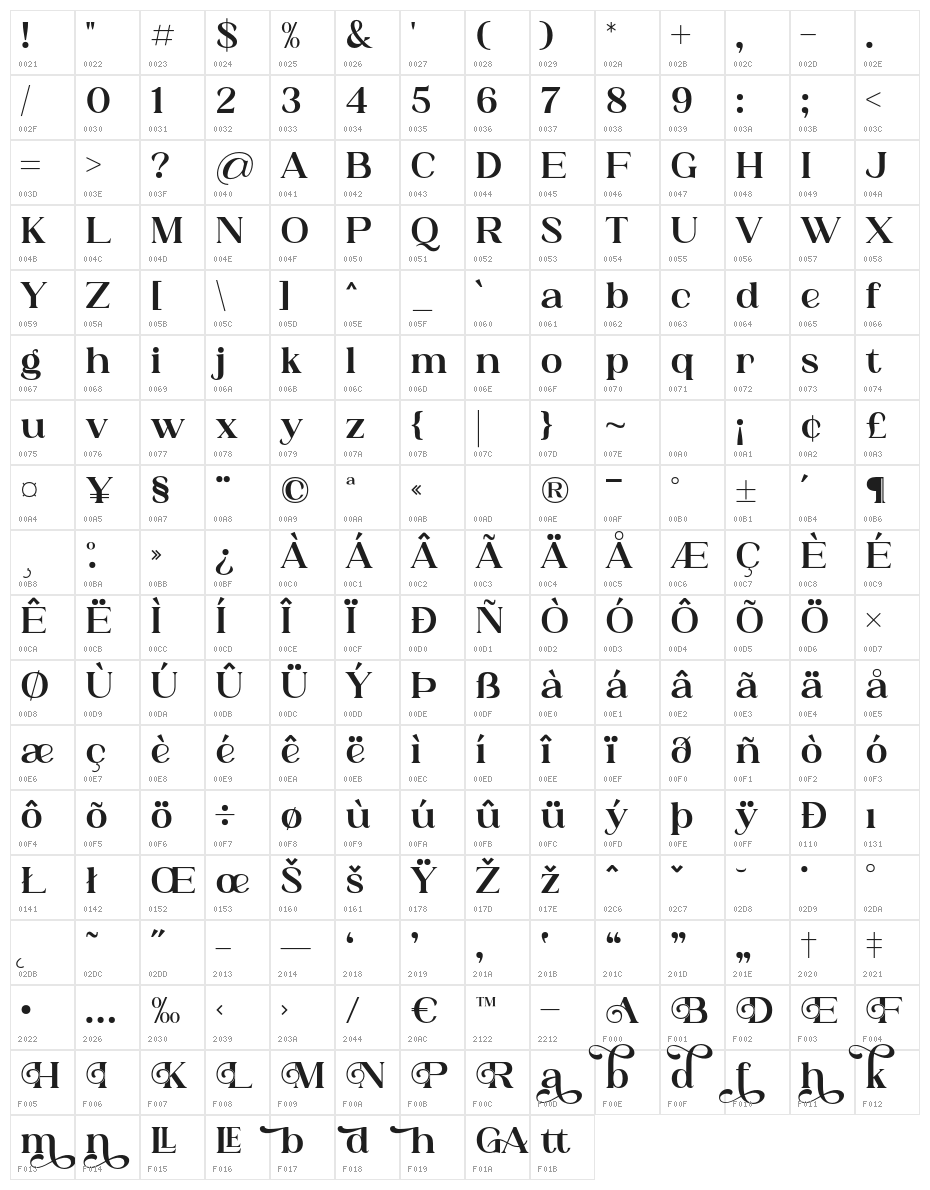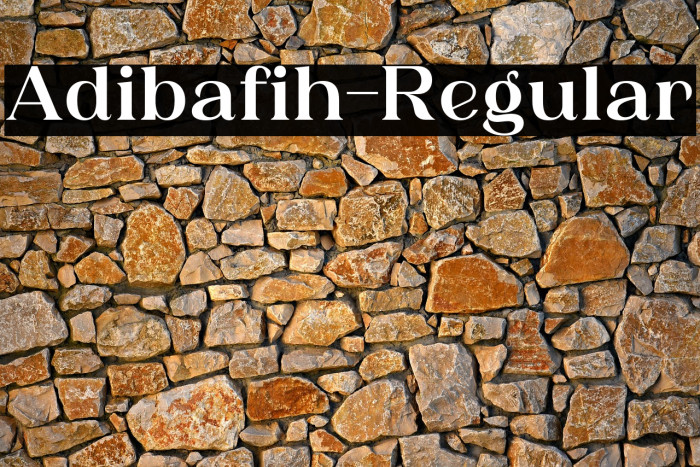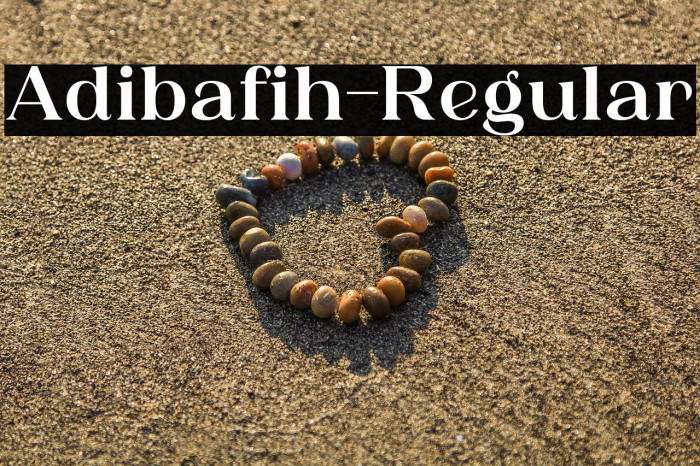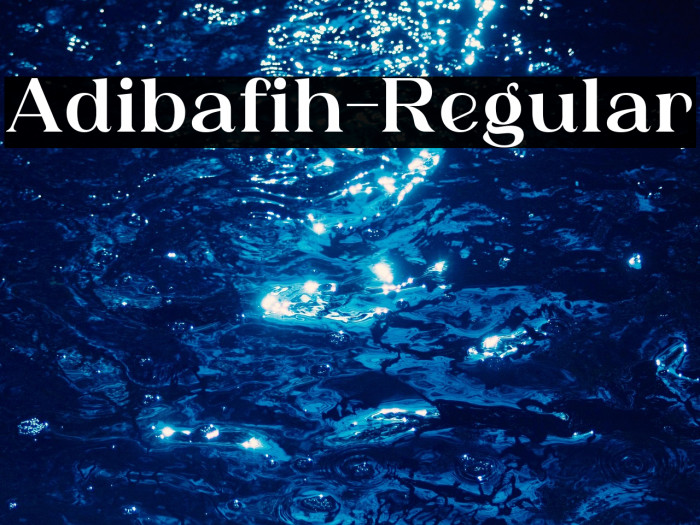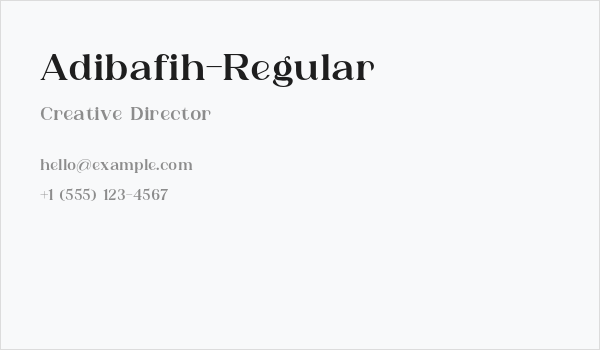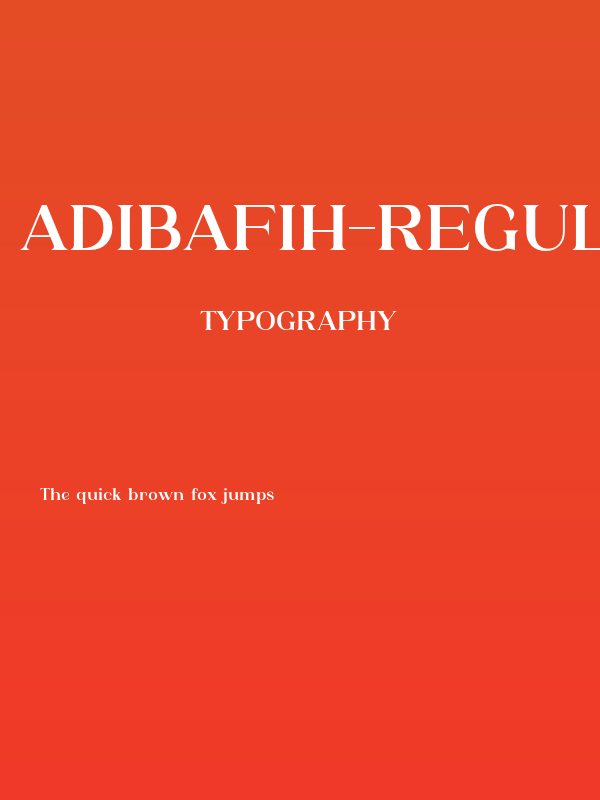
Adibafih-Regular Font
✎ Serif
يتضمن هذا الخط 254 حرفًا. انقر على أي حرف لرؤية التفاصيل.
| الفئات | Serif |
| النمط العام | Classic |
| حالة الاستخدام | Headlines, Body text, Logos |
| مشاريع مقترحة | Ideal for editorial design, book covers, formal invitations, and branding projects that require a touch of elegance. |